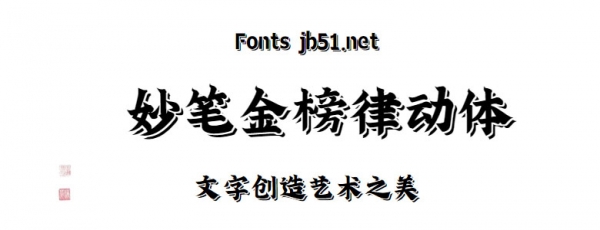
字魂妙筆金榜律動體是由字魂字庫推出的藝術(shù)字體,這款字體筆觸適中,字形端正,具有很好的視覺感,適合應(yīng)用于藝術(shù)設(shè)計、平面宣傳設(shè)計、網(wǎng)頁設(shè)計,書法字帖等領(lǐng)域。
妙筆金榜律動體字體是一款可商用的裝飾字體,該字體包含6763個中文、字母、 符號和數(shù)字,具有時尚的風(fēng)格,可以滿足您設(shè)計上的各種需求,該字體主要用于標(biāo)題等場景, 您不但可以在字魂網(wǎng)下載妙筆金榜律動體字體,同時還有眾多毛筆書法字體、創(chuàng)意字體等可供選擇!